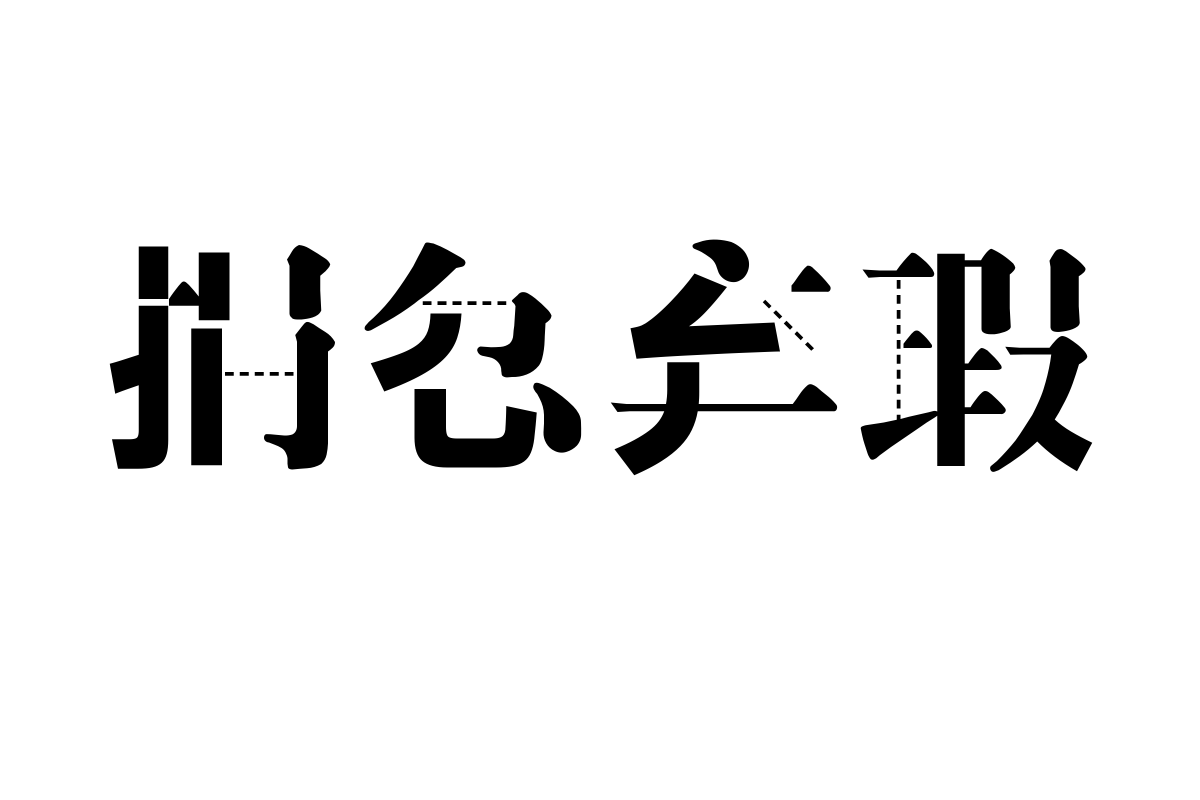
**汉仪阿尔茨海默病字体是一款具有公益性质的字体,旨在通过视觉艺术的形式表达对阿尔茨海默病患者的关怀与支持**。
这款字体的设计灵感来源于阿尔茨海默病患者认知能力减退和记忆缺失的现象,通过字体风格的变化来直观地传达这一信息。字体设计师们历时1个月,从理念剖析、系统设计、结构整合等方面高强度协作完成了“汉仪阿尔茨海默病体”。这种字体不仅覆盖了常用汉字,还包括数字、标点、拉丁文等将近7000个字符,为人们提供了丰富的文字选择。